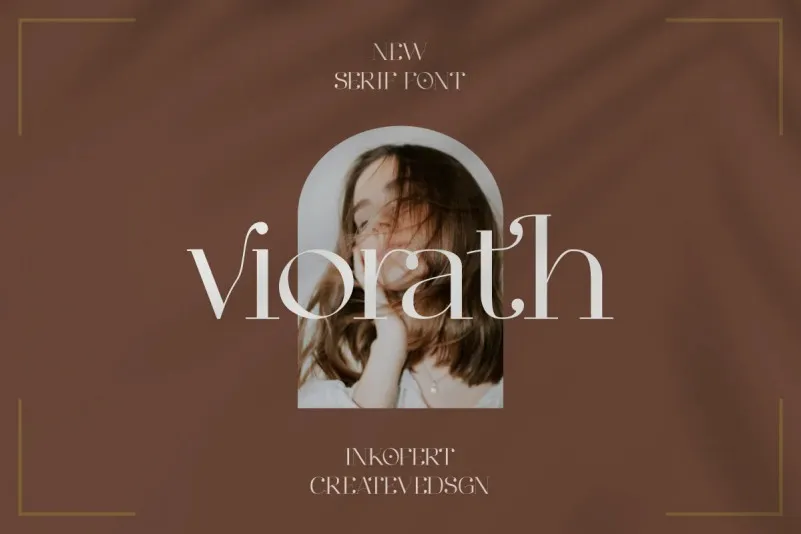
A Viorath Font é uma elegante tipografia serif que traz o contorno firme dos tipos normais. Ideal para projetos visuais requintados e sofisticados, essa fonte combina a modernidade com um toque vintage. Desenvolvida e compartilhada pela equipe da Inkofert Createvedsgn, ela é perfeita para criações como logotipos memoráveis, posts de blog inspiradores, identidades de marca e até cartões de casamento. Suas ligaturas sofisticadas permitem a criação de designs impactantes que se adequam à ampla gama de usos sugeridos – desde as redes sociais até imagens para revistas. Com sua personalidade única e estilo elegante, a Viorath Font é uma escolha perfeita para aqueles buscando um toque sofisticado em qualquer projeto visual. Suas linhas suaves e detalhes meticulosamente criados tornam cada letra uma obra de arte, ideal tanto para estilos tradicionais quanto para os mais modernos. Essa fonte é uma ótima opção para criar mensagens memoráveis que capturam a atenção do público, seja em um design de logotipo ou na elaboração de qualquer texto visual relevante.